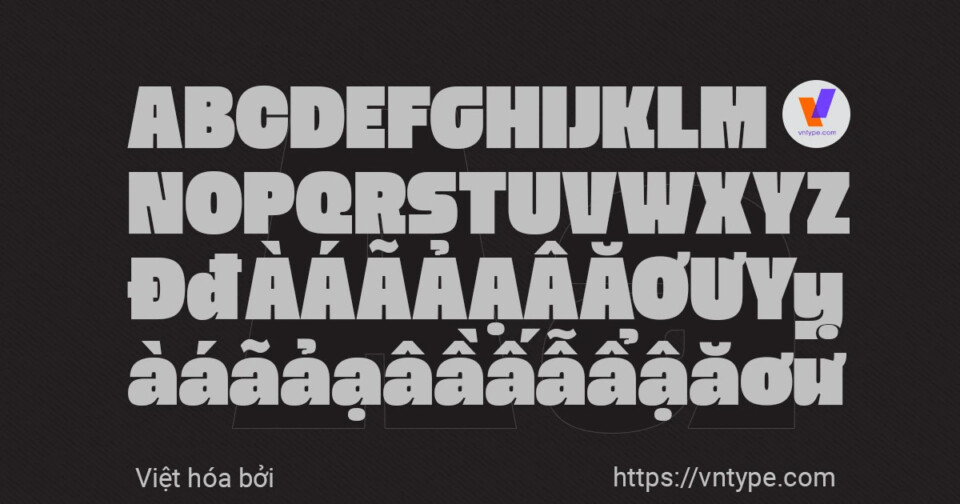
Font Việt hóa TF Runking Semibold – Font cho thiết kế bóng đá, thể thao
Tên font: Font Việt hóa TF Runking Semibold – Font cho thiết kế bóng đá, thể thao
Tác giả: FontVietHoa.Org
Font Việt hóa TF Runking Semibold là font chữ cứng cáp, mạnh mẽ. Font phù hợp với thiết kế thể thao, thiết kế chữ cho áo bóng đá